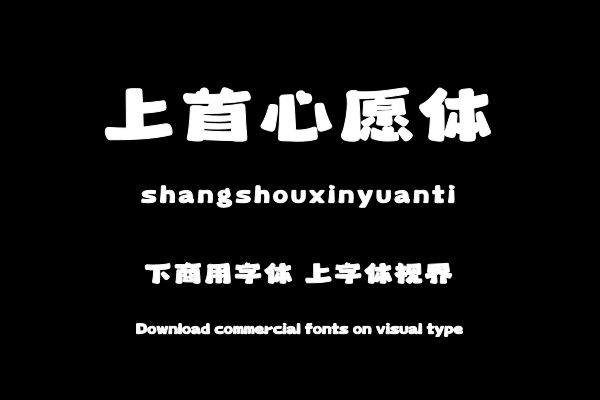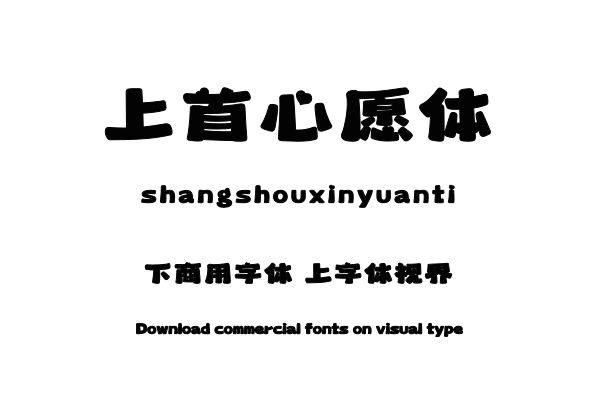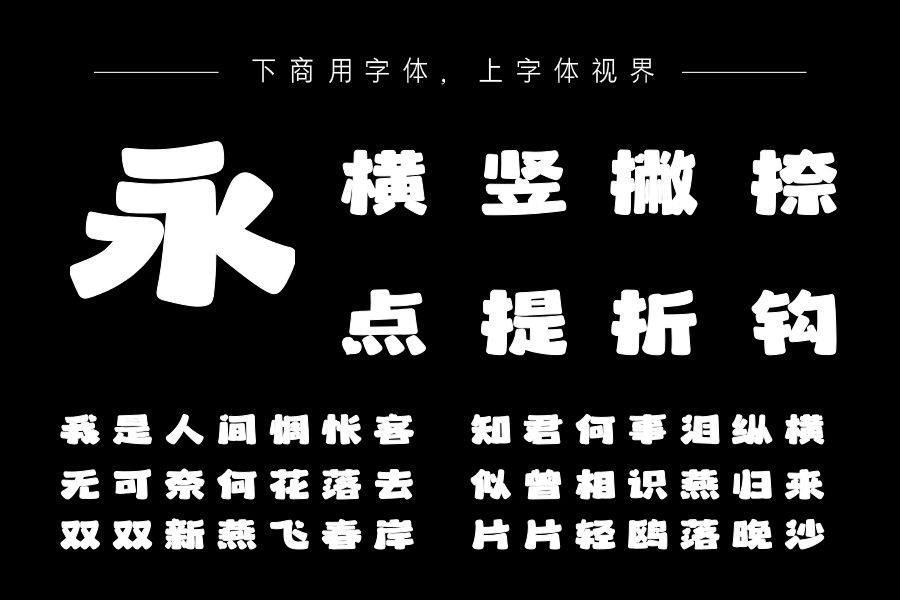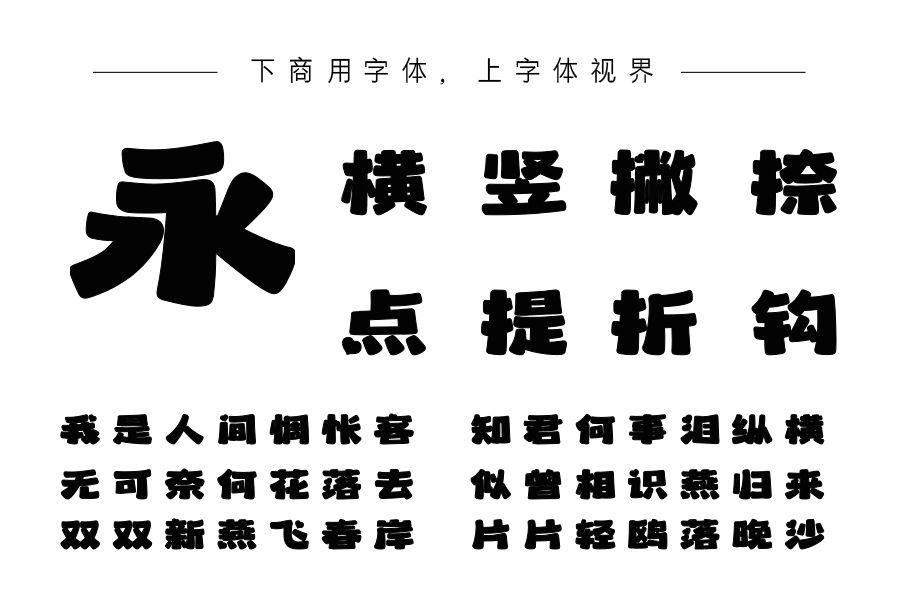
上首心愿体,字体以严格统一的网格保持大小一致,形态稳重整套字体笔画多样化,比较随意,但在笔画之间的搭配上又保持统一感,把“爱心”作为笔画“点”的设计,给字体带来......购买须知:“下载服务费”与“字体VIP”所获得字体 仅用于个人非商用, 商用请联系付费授权。本字体为电脑用字,手机没有root权限不支持直接手机换字(手机如何root,请自行百度搜索教程)。购买前请先 了解清楚后再付款 ,字体为虚拟产品无法回收 一旦购买不支持退款。